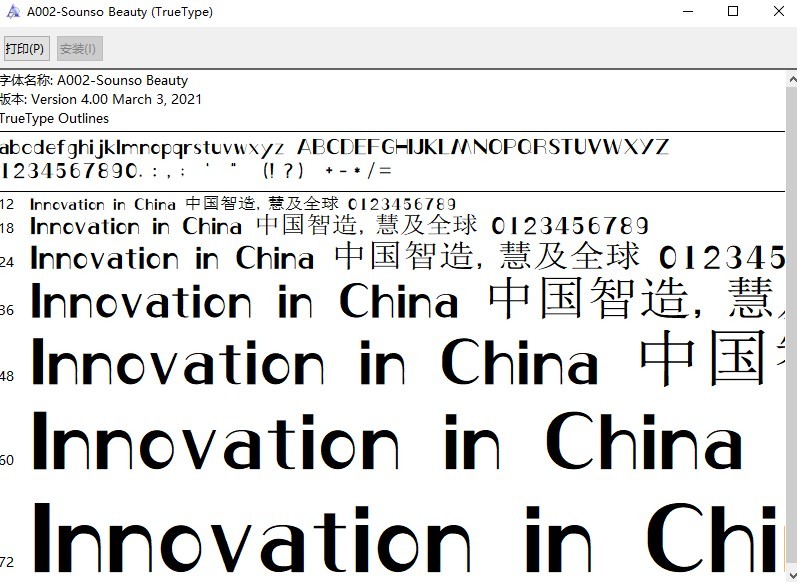
sounso beauty字體是英文字體中比較受歡迎的一款字體。這個(gè)字體輸出的英文內(nèi)容非常美觀,多用于設(shè)計(jì)一些海報(bào)、雜志以及印刷等等。在大家進(jìn)行版面制作的時(shí)候可以嘗試使用sounso beauty字體進(jìn)行設(shè)計(jì),整體效果絕對(duì)讓你滿意!
Sounso Beauty字體是一款適用于廣告設(shè)計(jì)方面的字體!